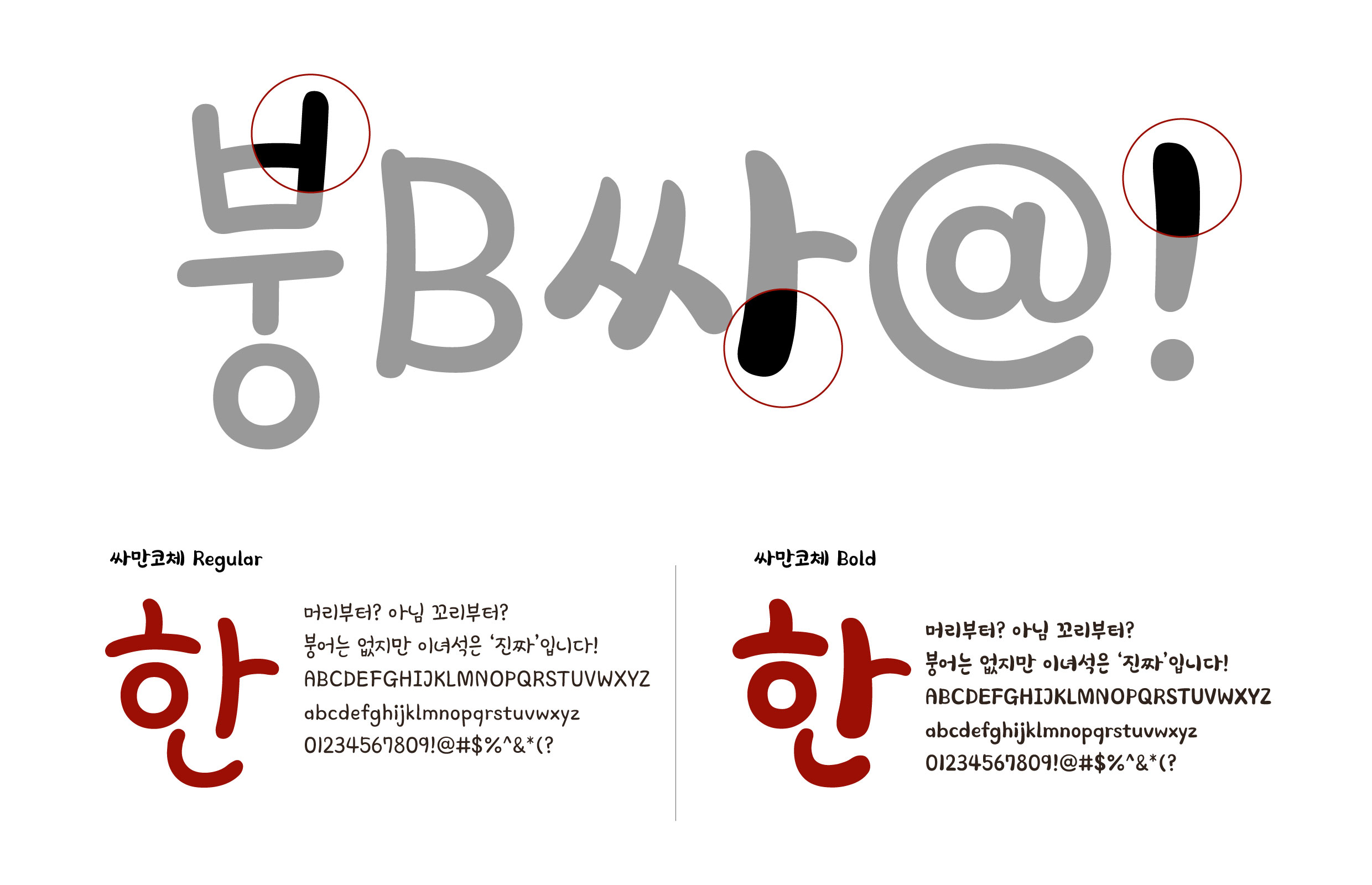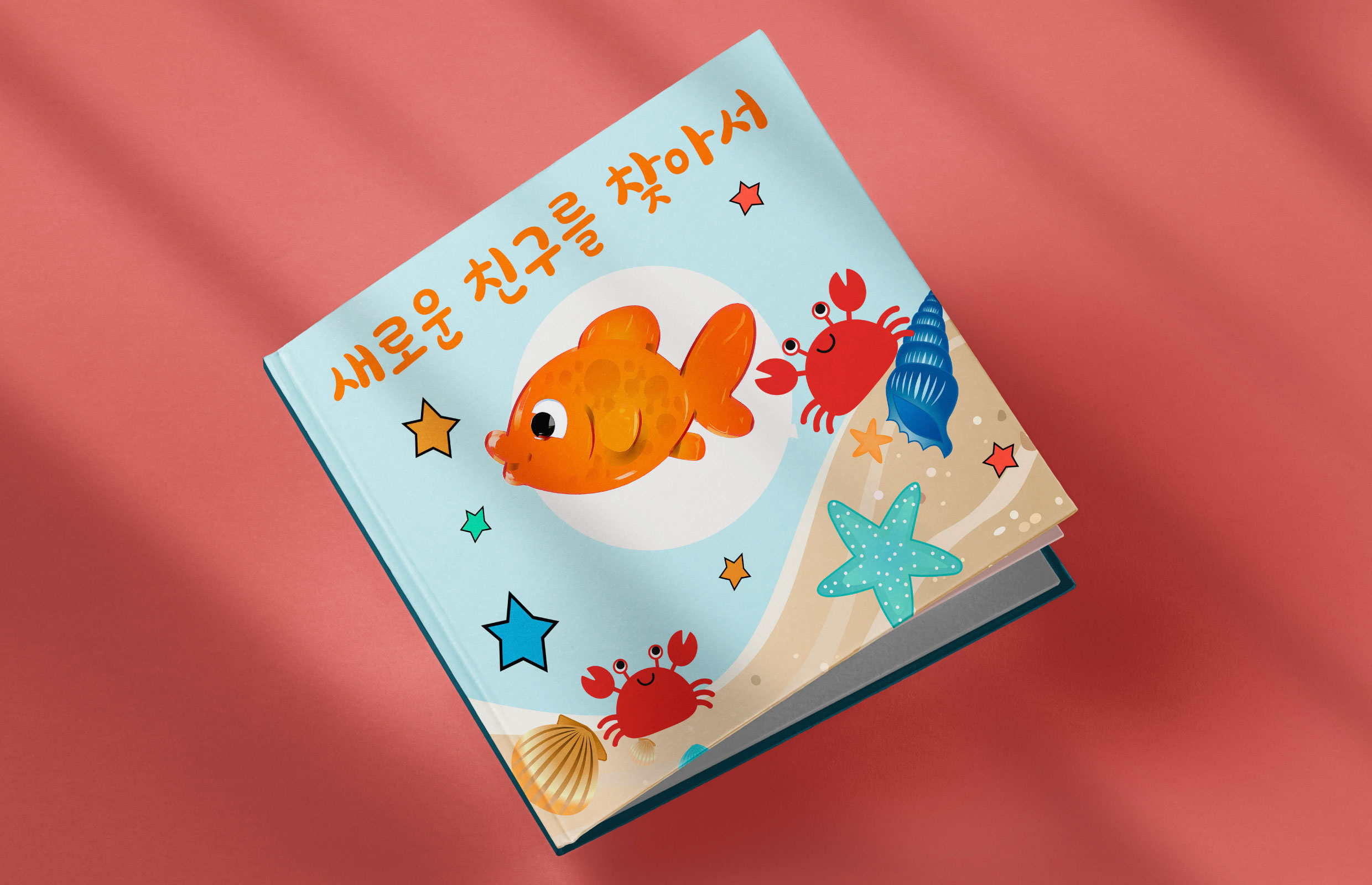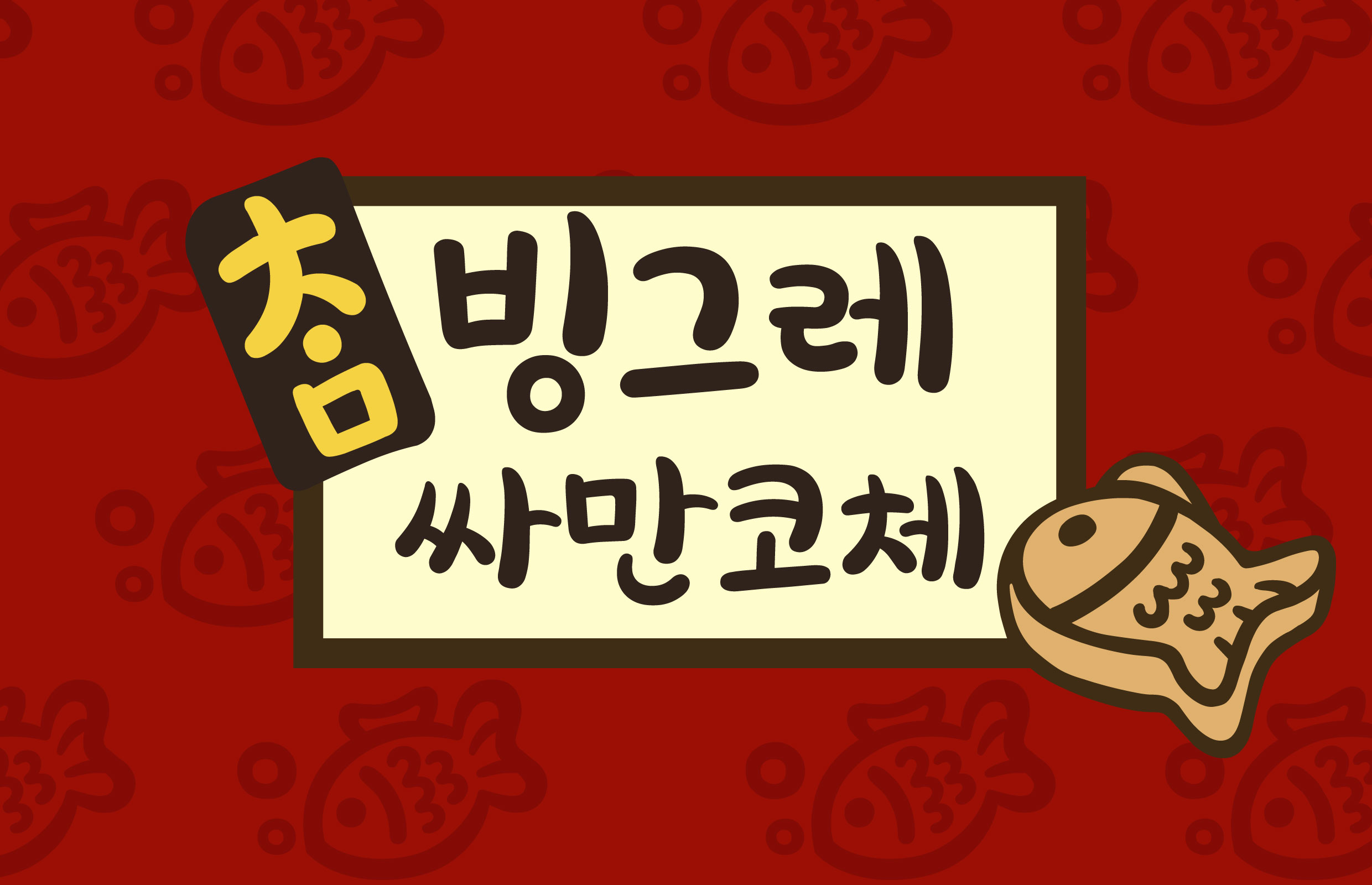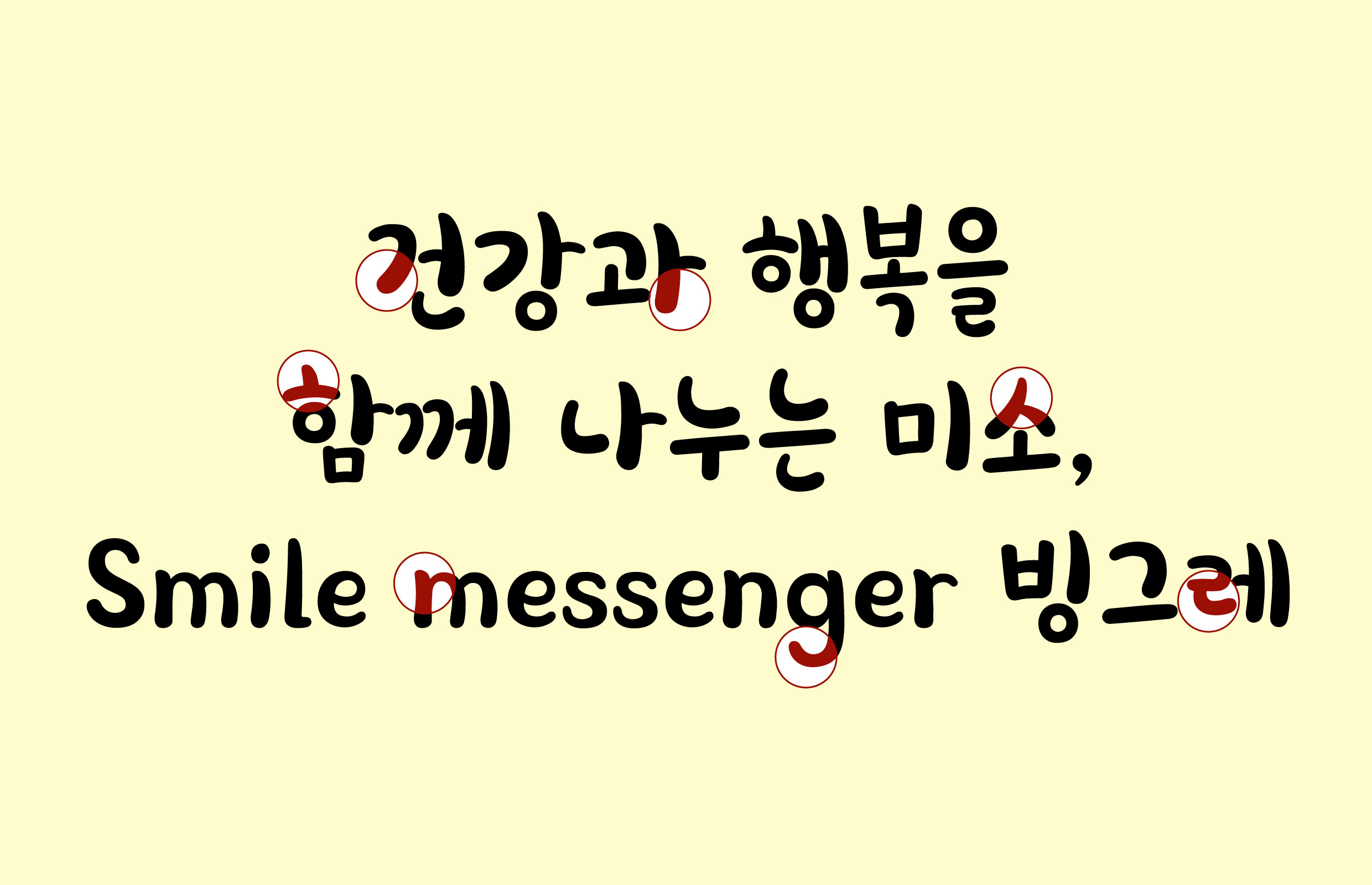
빙그레 [싸만코]
2016년 빙그레체, 2017년 빙그레체Ⅱ, 2018년 빙그레 따옴체, 2018년 빙그레 메로나체에 이은 다섯 번째 빙그레체 시리즈. 빙그레의 아이스크림 제품 ‘붕어 싸만코’를 테마로 한 서체다. 전문 캘리그래퍼의 손글씨 원도를 바탕으로 제작하였고, 아이스크림 형태를 표현한 이모티콘인 ‘붕싸티콘’을 함께 개발하여 사용의 재미를 더했다.